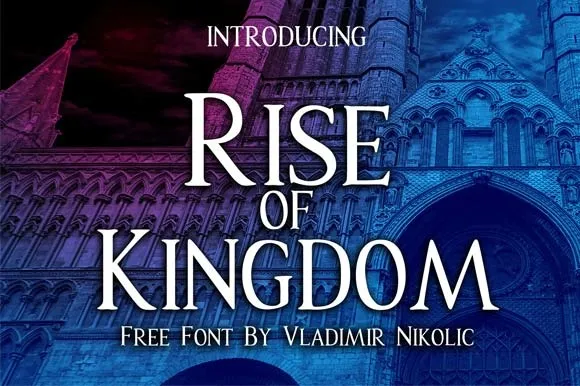
Rise of Kingdom Font – Fonte Grátis
Rise of Kingdom Font
A fonte Rise of Kingdom é uma elegante escolha para designers aventureiros que buscam um estilo sério e bem-balanced. Desenvolvida pelo designer Hamilton, esta serif é perfeita para aquelas criações mais elaboradas como posters, logotipos, citações, cabeçalhos de página, etiquetas de rótulos ou embalagens. Com seu design fluido, a Rise of Kingdom oferece uma variedade completa de caracteres incluindo letras maiúsculas e minúsculas, números, pontuação, ligaduras, alternativas, caracteres internacionais e até mesmo um monte de gráficos clip art para tornar seus projetos ainda mais vivos. Esta font é ideal tanto para profissionais quanto para iniciantes, uma vez que é livre de custo e sua liberação gratuita vem da Creative Fabrica. Que tal adicionar esta elegância ao seu próximo projeto?